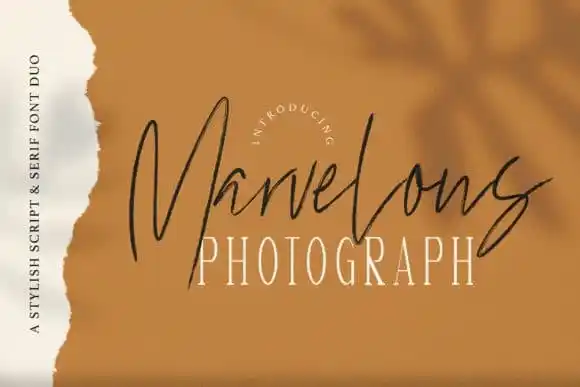
Marvelous Photograph Script Font Duo – Download Grátis
A Marvelous Photograph Script Font Duo é uma escolha perfeita para quem busca transparência e elegância no design digital. Composta por duas tipografias modernas: serif e script, esta dupla de fontes foi criada pelo talentoso font designer StringLabs. Este duo de fontes atinge o nível mais alto em qualquer projeto gráfico onde a simbiose entre texto e imagem é crucial. A Marvelous Photograph Script Font Duo combina um ar elegante com uma delicadeza moderna, oferecendo grande versatilidade para que você possa adaptá-la ao seu trabalho de design em diversas áreas. Essas fontes são perfeitas para criar logos, dar vida a postagens nas redes sociais e até mesmo confeccionar convites. O poder desta dupla de fontes é inegável; elas trabalham tão bem juntas que podem transformar qualquer ideia criativa em algo realmente especial. Agora é a hora de explorar o potencial de uma nova versão do seu design, com Marvelous Photograph Script Font Duo, para torná-lo ainda mais impressionante. Essa dupla de fontes será sua melhor aliada na jornada de desenvolvimento e criação visual.